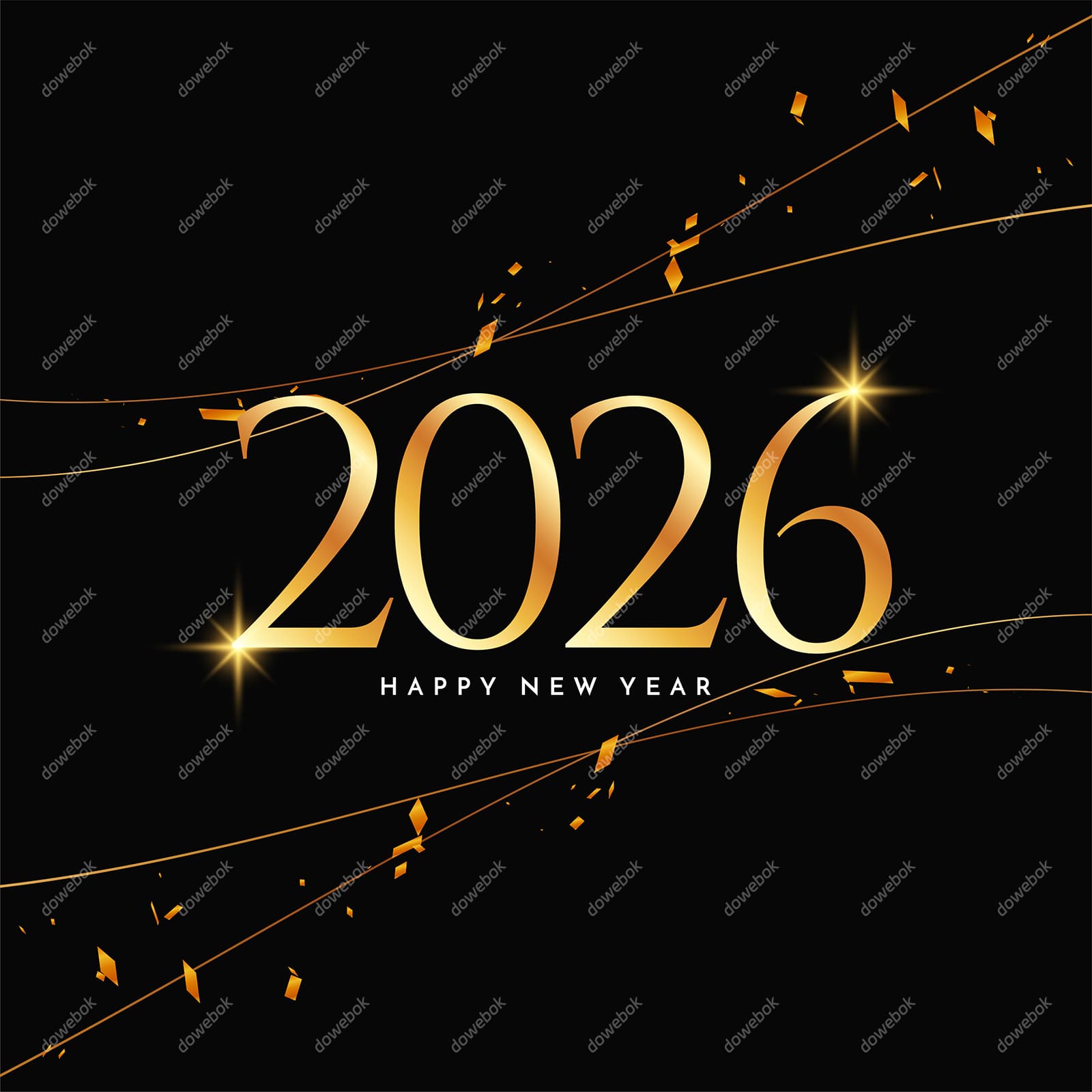
这是一款金色线条和数字设计的 2026 新年快乐矢量素材,纯黑背景上,金色 “2026” 字体泛着光泽,搭配 “Happy New Year” 英文,简约醒目。金色线条如丝带交织,点缀着碎金箔与星芒光效,营造出烟花绽放般的动感氛围。整体黑金色调高级奢华,线条与金箔元素既显新年的热烈,又传递出精致的仪式感,视觉冲击力强。